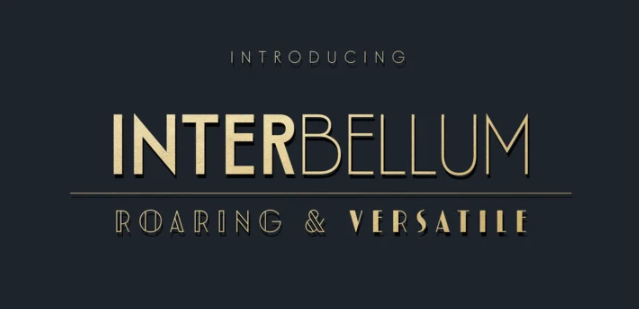
[Myfonts] Interbellum Font (2021)
Myfonts Interbellum Font (2021)
Interbellum - это семейство шрифтов в стиле ар-деко, которое содержит 3 дисплейных шрифта, 2 современных текстовых шрифта и 4 шрифта AllCaps. В сочетании друг с другом вы можете легко придать своему дизайну смелый, но элегантный вид. А благодаря использованию множества различных наборов стилей, шрифт способен занять достойное место в любом дизайне.
Хотя он был вдохновлен ревущими 20-ми годами, мы по-прежнему считаем Interbellum вечным путешественником во времени, который обязательно произведет впечатление на ваших клиентов.